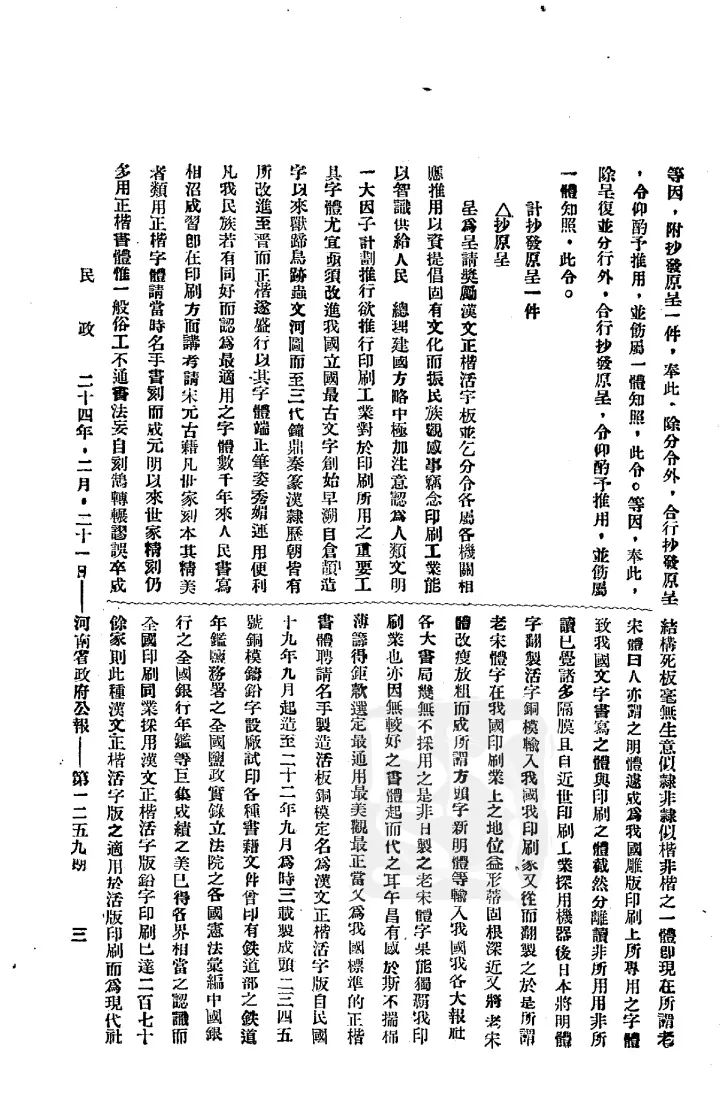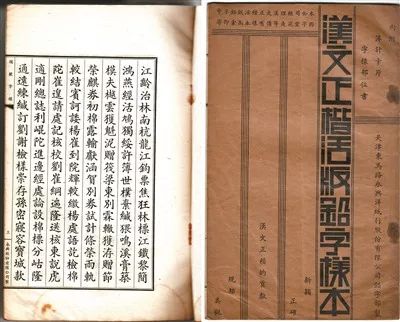
汉文正楷 新发明大革命
—郑午昌与汉文正楷印书局
“书写之体与印刷之体截然分离,读非所用,用非所读” ,这是近百年前一位有心人对于出版物中宋体字一统天下发出的慨叹。
这位有心人,就是郑午昌。
1935年1月29日,一篇题为“呈请奖励汉文正楷活字板,并请分令各属、各机关相应推用,以资提倡固有文化而振民族观感事”的呈文递至国民政府。
这篇呈文粗看洋洋洒洒,细审句句精心。开篇以孙中山对于印刷业的重视作为前引,把印刷字体提高到了“建国方略”的高度,接下来从多方面论述汉文正楷为汉民族正统的、经典的文化地位,请求政府表彰汉文正楷字体,向全国推广使用。
这篇呈文的作者,便是郑午昌。
郑午昌呈请奖励汉文正楷活字板
汉文正楷活字诞生,这一被众多爱国人士赞誉为“我国印刷工具之新发明,现代化事业之大革命”,被蔡元培先生誉为“中国文化事业之大贡献”的故事,发生在十九世纪三十年代的上海。 故事的主角,当然是郑午昌。 思考 审美学方面的考虑 近代以来长期在出版物中占据优势地位的是宋体字。宋体字横平竖直,字画一律,既便于阅读,又利于刻板,使得刻字效率大大提高,但美学角度而言,相对机械呆板,有形无神。 与宋体字相对的,是相对于平正呆板的所谓‘匠体字’而言手写上版的楷体字,匀整有致、垂范书林。 晚明后二百多年时间里,两者曾并驾齐驱,各擅胜场。但总的来说,软体字对于书手、刻工的要求均较宋体字高出许多,工价也较昂贵,故而日渐稀少。 宋体字的流行牺牲了印刷字体审美上的丰富性,更严重的是使得写字和读书成为相互隔离的两件事。 改良印刷字体,在有识之士看来势在必行。 民族自尊心方面的考量 其一,我国雕版刻书有优良的传统,宋元以来字体美观、刻印上乘的雕版书,皆用楷字。给国民政府的呈文中,他深情阐述“至晋,正楷遂盛行。字体端方,笔姿秀媚 运用便利。凡我民族,共有同好而认为最适用之字体。”印刷方面讲,“考诸宋元古籍,凡世家刻本,其精美者类用正楷字体,请当时名手书刻而成。元明以来,世家精刻仍多用正楷书体。” 其二,我国铅印汉字初创之始,设备、技术、人才、资金处处受制于外人,字体的设计、字模的铸造也不例外。19世纪中后期,通行于国内的就是日本筑地式铅字,即所谓的“筑地体”和“秀英体”,实际均仿照晚明的宋体字设计,它虽然易于书写,便于刻铸,而且有成套大小不同的七种字号,但“好古者憾其不精审美,习而生厌”。 敏求于古,从本国悠久丰富的雕版史中寻找设计灵感,在有识之士看来也是万不容缓; 其三,十九世纪以来,汉字制版印刷现代化的主动权一直在西方资本家手里,中国人从事相关事宜受掣肘受气是经常发生的事。午昌先生当时与海上画家组织中国画会、蜜蜂画社,出版《蜜蜂画报》,与独家拥有正楷字模的外商美灵登印刷厂有业务接洽,厂方傲慢无礼,居奇要挟,排印之事上种种留难。更有甚者,言语间以中国人不会制造中国字样论调多有嘲讽,引发先生极度不满; 做中国人自己的汉字制版印刷,郑午昌果断行动 他草拟制造铜模计划,写了创制正楷字模的意见书,向中华书局求助建议。奈何当时的中华书局正在添制仿宋夹注字(长体)和仿宋注间连积字,无论在资金、人力、工厂设备等方面无暇顾及,委婉搁置。 商议未果,他决定招股自办企业,铸造楷字。得到他众多同道好友李祖韩、陈小蝶等人的赞成和支持,1932年,汉文正楷印书局股份有限公司在上海正式成立,设总局于山东路,设印刷厂于杨树浦华盛路三益里。郑午昌任总经理。 他请来当时精于馆阁体的的书法家高云塍设计字体,书写了近万个正楷常用字用于制作美观实用的铜模铸字;请来朱云寿、许唐生、陆品生、郑化生等高手刻字,制成一至六号字模各一副,疏体(字面较小)和足体(字面较大)两种。 自1929年开始制造,至1933年9月全部完工,历时三年有余。
影响
《汉文正楷活版铅字样本》, 约二十世纪三十年代
汉文正楷一经面市就受各界欢迎。
开始的三年中,书局承印的书籍、文件达25万种,全国先后有350余家印刷同业购买了汉文正使得楷活字使用。
1935年,因郑午昌的呈文,教育部规定汉文正楷为印刷教科书的字体。政府力量强有力的推广使得汉文正楷印书局业务迅速发展,除了自己承揽印刷业务,还在全国各地设立分号,并且向同行发售铅字。七七事变之前,汉文正楷印书局已在香港、南京、天津、广州、汉口、青岛、苏州等地设立了经理处。
抗战期间,因屡遭侵沪的日寇觊觎和欺压,郑午昌不顾一切,自动的把印刷工场全部毁坏,誓不屈伏合作。
民国版《标准草书范本-千字文》
上海汉文印书大开本
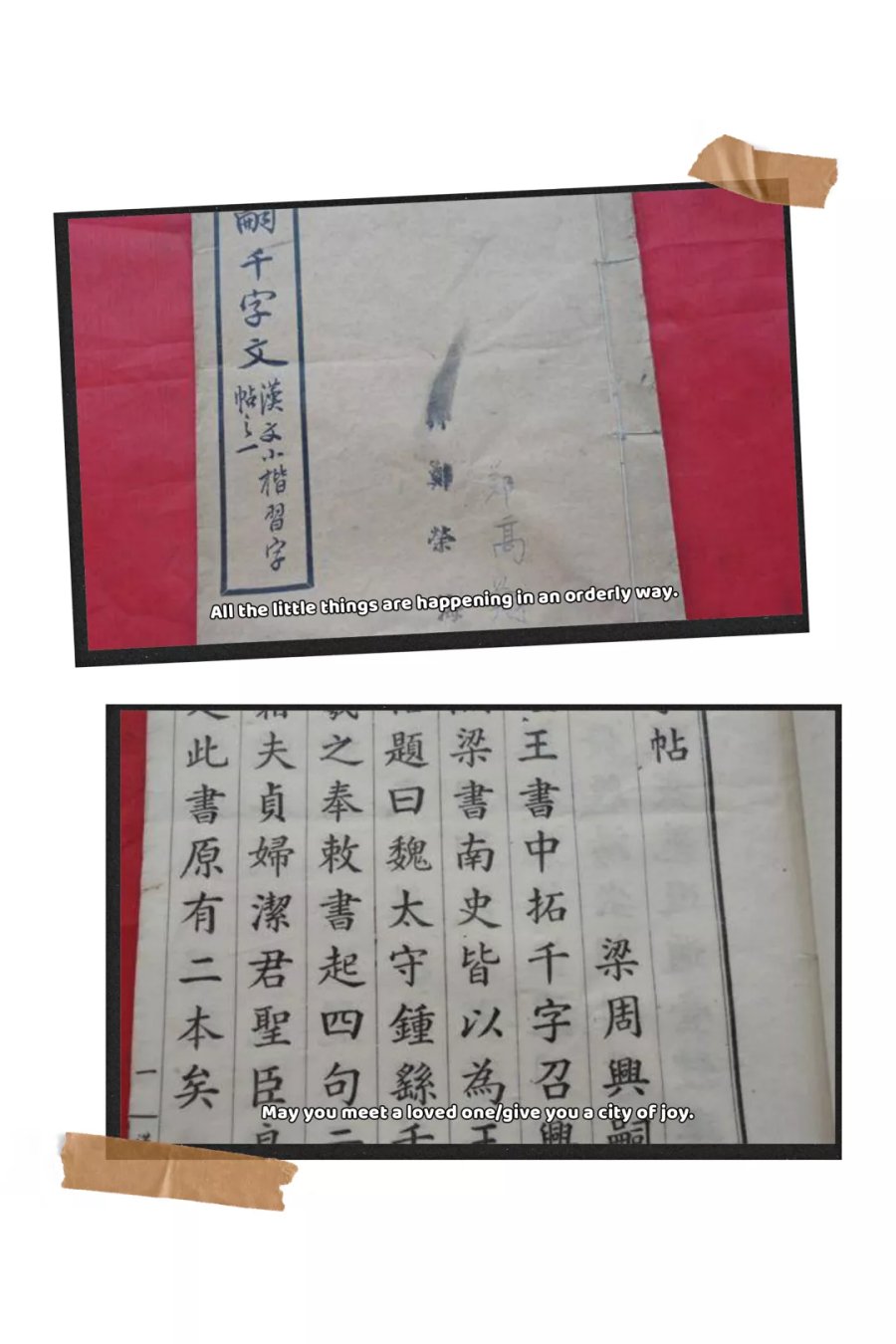
千字文小楷帖
(1934年汉文正楷印书局,白纸大字排印)
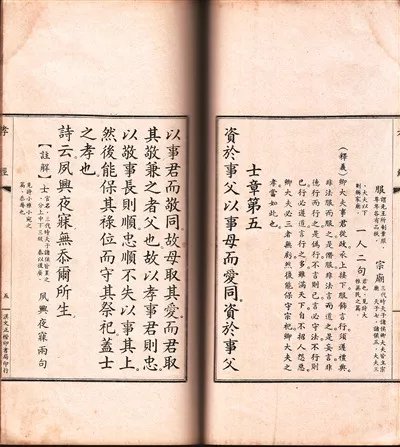
郑午昌为母祝寿刊印的越缦堂节注本《孝经》,线装,汉文正楷印书局1936年版
新中国成立后,汉文正楷印书局改名汉文铸字铜模厂。身影逐渐在历史中褪去,但汉文正楷字体在新中国的印刷出版事业中仍发挥着重要作用。直至20世纪90年代,汉文正楷字体仍应用于小学课本等出版物。
1992年中国印刷及设备器材工业协会编写的《印刷科技实用手册》中,对于楷体印刷体字有这样的介绍:“现在印刷体正楷有两种,即汉文正楷和华文正楷。汉文正楷字形端庄,定为小学教科书专用字体。“
1994年颁行的国标《印刷汉字字体分类》中,将印刷字体分为七类,还规定了不同字体的应用范围,楷体系列字体有两种,其中就有“汉文正楷”,适用范围是“小学课本、儿童读物、刊物标题”。
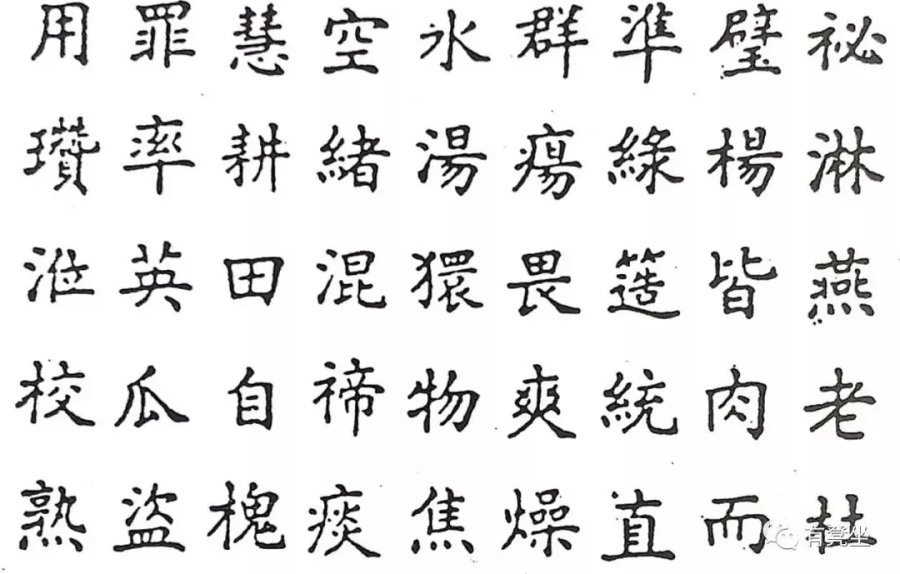
汉文正楷印书局“汉文正楷”
方正字库的汉文正楷字体
回顾历史,郑午昌等人苦心孤诣创制、使用汉文正楷字体的努力,或许并没有扭转宋体字在印刷物中占据优势的局面,但他们坚持国人自主设计字体,在字体的审美性、丰富性上做出的有益探索非同寻常,值得书写。
记住这个名字,郑午昌。
他所设计铸造的字体,名为汉文正楷。
他开创的事业,名为汉文正楷印书局。